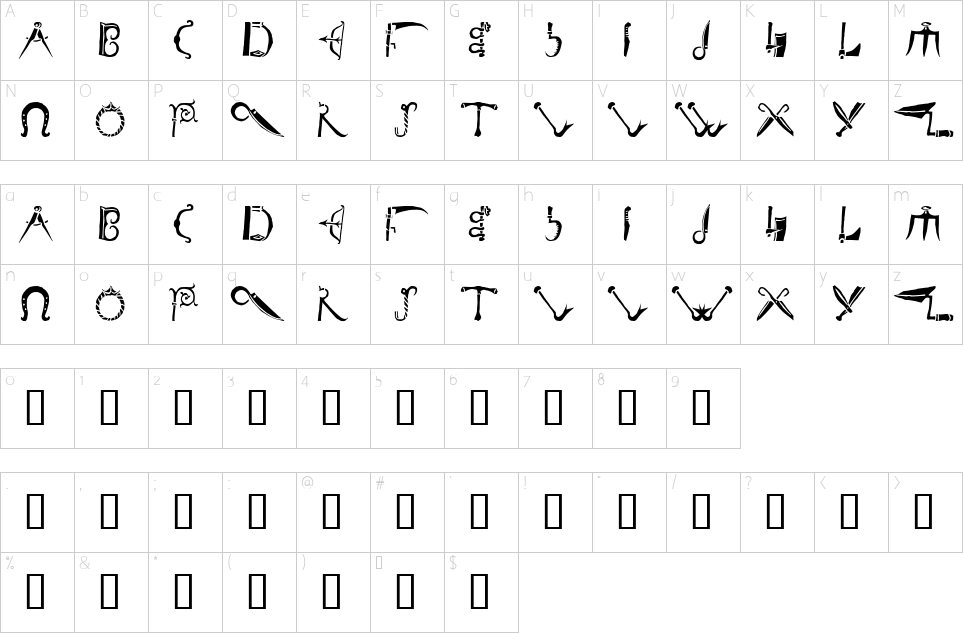
Descubra a elegância da De Balme Font para seus projetos digitais brasileiros. Desenvolvida por David Rakowski, esta fonte está disponível tanto para sistemas Windows quanto Mac. Seu design sofisticado é uma opção ideal para quem busca um equilíbrio entre modernidade e elegância em suas criações digitais. Com apenas 2.382 downloads no total, a De Balme Font se torna ainda mais especial – um tesouro de fontes gratuitas que você pode explorar sem restrições. Seja para criar cartazes publicitários, projetos gráficos ou até mesmo mensagens digitais, esta fonte traz consigo uma atmosfera natural e envolvente, aprimorando seu trabalho com um toque autêntico e sofisticado. Faça o download agora e dê vida ao seu design com essa fonte única e de qualidade.